Шрифт с засечками или без: что выбрать для разных задач
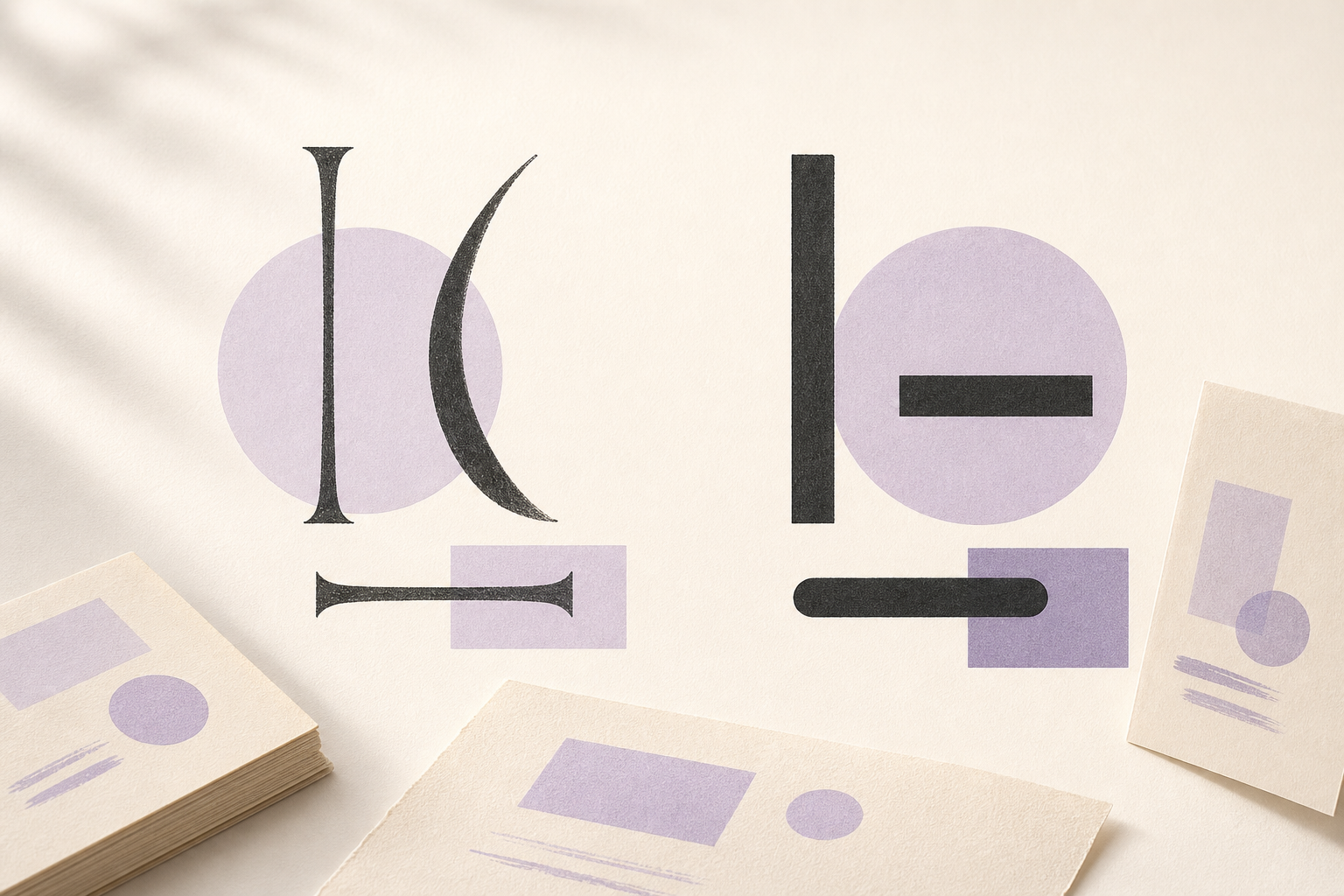
Шрифт с засечками или без: что выбрать для разных задач
Шрифт с засечками выбирают, когда нужны традиционность, литературный характер и выразительная фактура текста, а шрифт без засечек — когда важны ясность, компактность и современное звучание. Однако универсального правила нет: решение зависит от носителя, размера текста, длины строк, контраста, аудитории и общего стиля проекта.
В этой статье разберём различия между антиквой и гротеском, сравним их для сайтов, интерфейсов, печати, логотипов и рекламы, а также покажем, как проверить выбранную гарнитуру на практике. Материал актуален на 22 июля 2026 года.
Чем отличаются шрифты с засечками и без них
Засечки — небольшие завершающие элементы на концах штрихов букв. Гарнитуры с такими деталями традиционно называют антиквой. В них часто заметны различия между основными и дополнительными штрихами, характерный ритм букв и более выраженная каллиграфическая основа. Поэтому антиква может восприниматься как классическая, авторитетная, интеллектуальная или камерная.
Шрифты без засечек называют гротесками или sans serif. Их формы обычно проще: окончания штрихов не имеют дополнительных элементов, а рисунок букв выглядит более нейтральным и геометричным. Гротески ассоциируются с технологичностью, минимализмом, динамикой и функциональностью, хотя конкретное впечатление зависит от пропорций, толщины и деталей гарнитуры.
Важно различать классификацию и качество набора. Засечки сами по себе не делают текст более удобным, а их отсутствие не гарантирует хорошую читаемость. На восприятие влияют кегль, межстрочный интервал, длина строки, насыщенность, контраст с фоном и поддержка нужных языков, включая кириллицу.
Когда лучше выбрать шрифт с засечками
Антиква подходит для проектов, которым нужно подчеркнуть связь с культурой, историей, ремеслом или экспертным знанием. Её часто используют в книгах, литературных журналах, образовательных материалах, брендинге ресторанов, отелей, юридических и консалтинговых компаний. Выразительные засечки помогают создать характер уже на уровне заголовка или названия.
Для длинного печатного текста шрифт с засечками может быть удачным выбором благодаря заметному рисунку букв и устойчивому горизонтальному ритму строки. Но результат зависит от конкретной гарнитуры и качества верстки. Слишком тонкая антиква, мелкий кегль или недостаточный контраст быстро снижают комфорт чтения.
- Выбирайте антикву для книжного текста, эссе и материалов с литературным настроением.
- Используйте её в логотипе, если бренду важны наследие, премиальность или мастерство.
- Проверяйте, не теряются ли тонкие засечки в малом размере и на экране.
- Сочетайте выразительную антикву с нейтральным шрифтом для служебной информации.
Когда гротеск работает лучше
Шрифт без засечек чаще выбирают для интерфейсов, мобильных приложений, навигации, презентаций, рекламных объявлений и цифровых продуктов. Его лаконичный рисунок хорошо поддерживает короткие подписи, кнопки, меню и карточки, где пользователь быстро сканирует страницу, а не читает её последовательно.
Гротеск также удобен для брендов, которые хотят выглядеть открыто, современно и технологично. Однако нейтральный sans serif не всегда означает безликий дизайн. Ширина знаков, форма строчной а, открытость апертур, характер цифр и пропорции способны сделать гарнитуру дружелюбной, строгой, экспериментальной или деловой.
Для цифрового текста особенно важны экранные свойства шрифта: различимость похожих символов, устойчивость тонких элементов, наличие подходящих начертаний и корректная кириллица. Даже известная гарнитура может плохо работать в интерфейсе, если её формы рассчитаны на крупные заголовки, а не на компактные подписи.
Как выбрать шрифт для сайта и интерфейса
Для сайта сначала определите, как пользователь будет взаимодействовать с текстом. В блоге или медиа он читает длинные материалы, в интернет-магазине сравнивает товары, а в сервисе выполняет действия по подсказкам. Поэтому одна и та же гарнитура не обязана одинаково хорошо подходить для заголовков, основного текста, кнопок и числовых значений.
Для интерфейса начните с проверки кириллического набора, цифр, знаков валюты, кавычек, тире и специальных символов. Затем протестируйте текст в реальном размере: заголовок, абзац, поле формы, кнопку, уведомление об ошибке и длинное название товара. Оценивайте не отдельную букву, а весь ритм интерфейса и скорость поиска нужной информации.
- Определите основные сценарии чтения: быстрое сканирование, короткие действия или длинный текст.
- Выберите базовую гарнитуру и ограничьте число начертаний, чтобы интерфейс не выглядел хаотично.
- Проверьте набор на реальных русскоязычных фразах, а не только на латинском примере.
- Сравните варианты на светлом и тёмном фоне, включая состояния наведения, ошибки и отключённые элементы.
- Оцените ширину строк, переносы и визуальный вес текста на мобильном экране.
Вывод: выбирайте не классификацию, а задачу
Шрифт с засечками лучше раскрывается там, где нужны выразительность, традиция и литературный ритм. Гротеск чаще выигрывает в интерфейсах, навигации, рекламе и современных фирменных системах. Финальное решение принимайте по реальному макету, русскоязычному набору, размеру, носителю и роли текста.